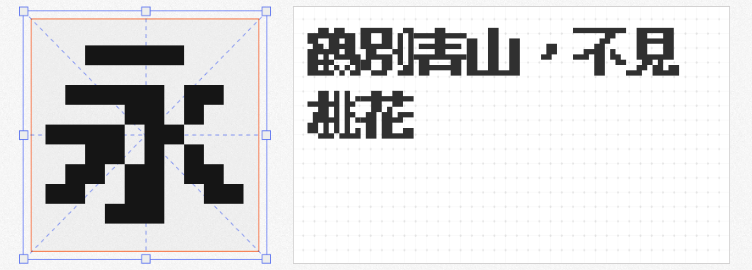
在“520”与情人节的浪漫氛围中,创意字体不仅是视觉的点缀,更是情感的载体。以下四款免费商用字体,以独特风格与情感张力,为你的设计注入甜蜜活力。
大宝桃桃体以“可爱”为核心,将笔画中的圆点部件替换为爱心符号,瞬间赋予文字童趣与温暖。这款字体笔画圆润、结构松散,自带无拘无束的萌态,适合母婴品牌、儿童动画或手账风格设计。其正文字体表现同样出色,即使大段文字也能传递天真烂漫的气息,让“520”海报瞬间充满治愈感。
仓耳非白以“黑与白”的强烈对比为视觉焦点,通过加粗主笔画与纤细线条的碰撞,形成硬朗而富有张力的字形。直角转折与直线撇捺的几何化设计,赋予字体前卫的科技感,而圆形点画的加入又中和了冷硬感,增添一丝柔和。这款字体适合科技感与时尚感并存的情人节主题设计,如情侣电子贺卡、极简风礼物包装,传递理性与感性交织的爱意。
仓耳与墨将传统篆刻的“刀刻感”融入现代字体,笔触如刻刀般苍劲有力,转折处却以圆角过渡,形成“内方外圆”的独特气质。5个字重的家族字体支持多场景应用,从主标题到副标题均可保持视觉统一。其配套英文与标点延续中文设计语言,适合国潮风、艺术展览或高端礼品包装,传递厚重而不失柔情的文化底蕴。
觉得情人节的设计千篇一律?试试这款这款基于点阵风格改作的字体吧 !它以9×9像素网格构建字形,复古感与科技感并存。笔画粗细统一,方格结构自带游戏机、像素艺术的怀旧气息,而新增的颜文字符号与直排特性,更贴合年轻群体的表达习惯。适用于情人节游戏界面、像素风插画或社交媒体表情包,用极简像素传递“爱意加载中”的俏皮感。
无论是萌系爱心、极简几何、篆刻刀意还是像素复古,这四款字体均以免费商用为前提,为“520”与情人节设计提供多元选择。用字形诉说爱意,让每一份作品都成为独一无二的浪漫表达。